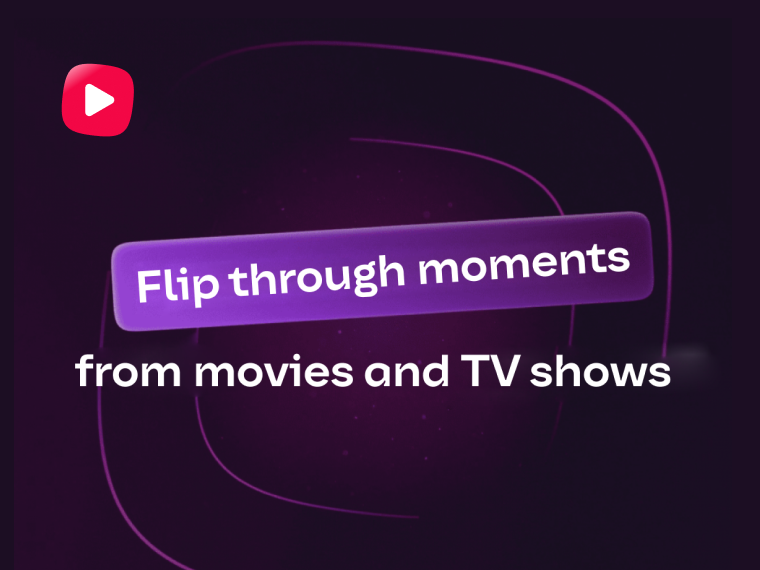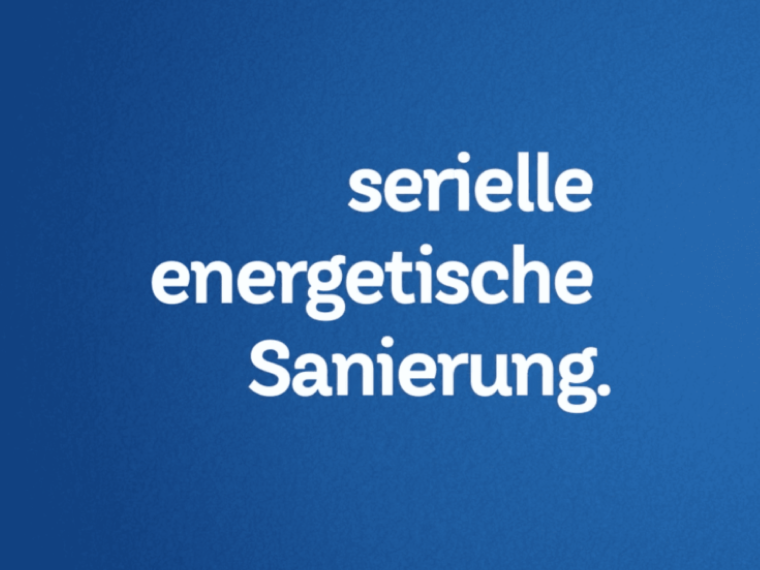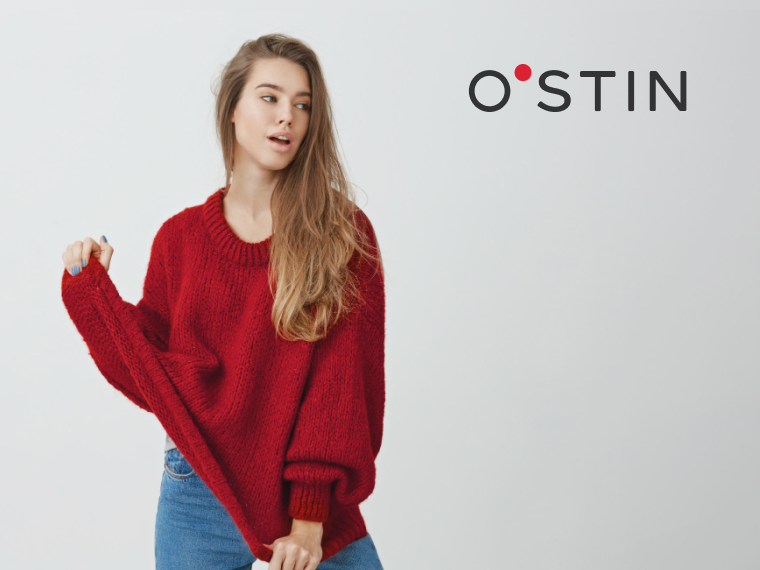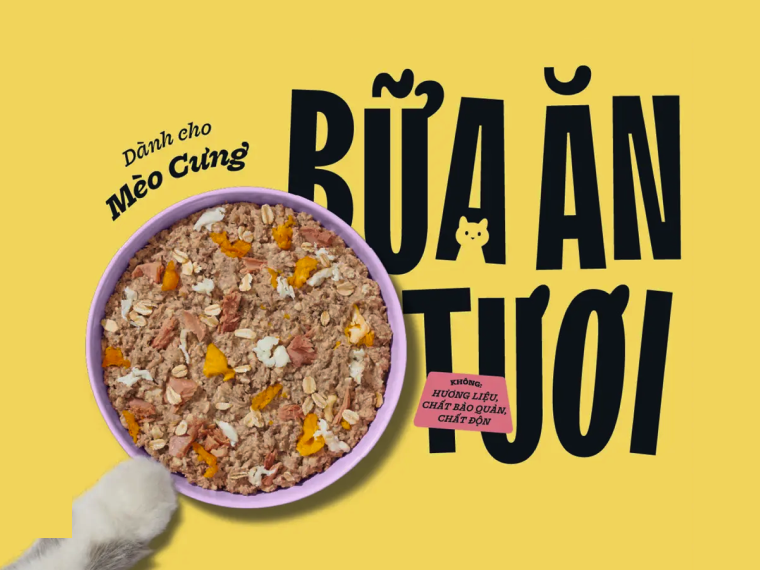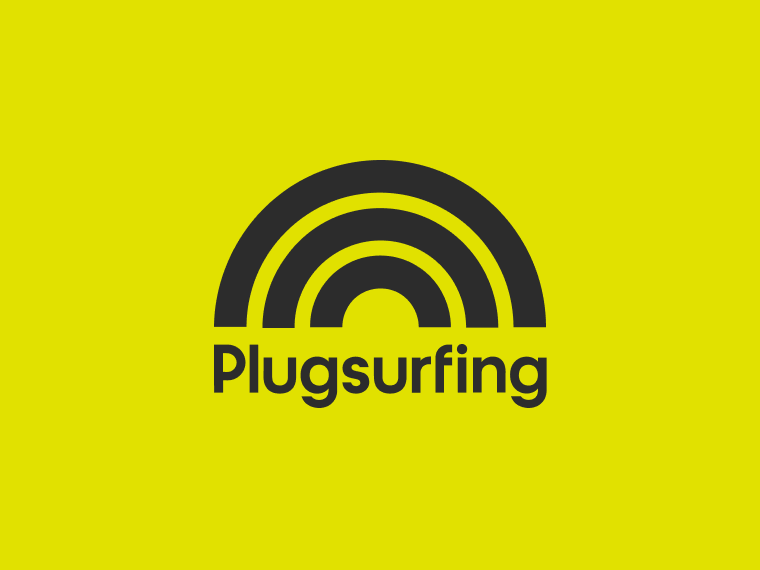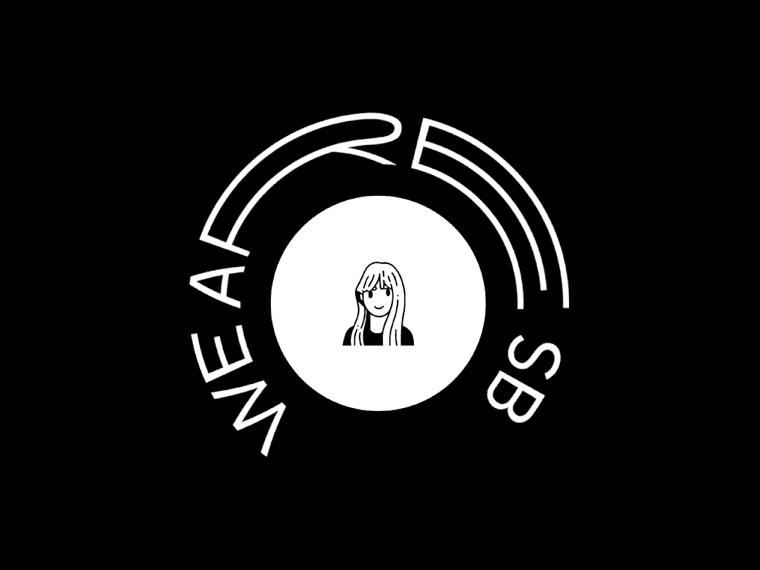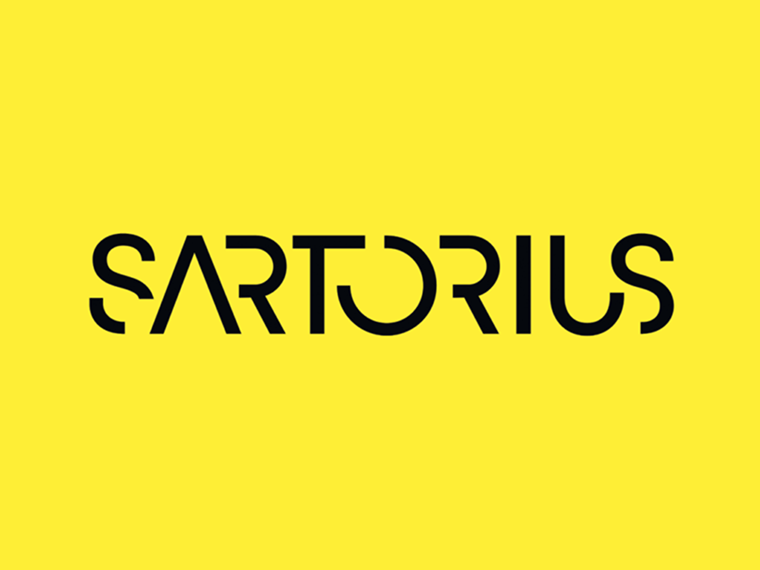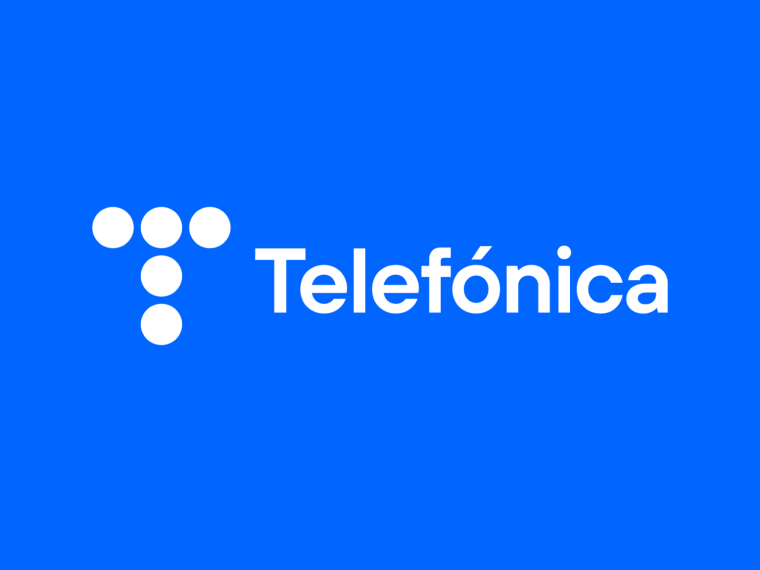
Fonderie Polices sur mesure
La voix de votre marque en typographie
Nous pouvons adapter n’importe quelle police TypeType pour qu’elle corresponde parfaitement à votre projet ou concevoir une typographie entièrement nouvelle qui incarne les valeurs de votre entreprise.
Options de personnalisation
Personnalisation légère
• Renommage de la police
• Ajout d’un logo au jeu de caractères
• Remplacement des caractères principaux par des alternatives
• Modification graphique de glyphes individuels
Personnalisation standard
• Renommage de la police
• Ajout d’un logo au jeu de caractères
• Modification graphique de glyphes individuels
• Création de nouveaux styles
Personnalisation avancée
• Renommage de la police
• Ajout d’un logo au jeu de caractères
• Croquis
• Modification graphique de glyphes individuels
• Conception d’une police basée sur une police TypeType
Création de police sur mesure
• Nom unique de la police
• Ajout d’un logo au jeu de caractères
• Croquis
• Création d’une police personnalisée
• Ajustements techniques: mastering, kerning, hinting, fontinfo
Personnalisation légère
Choisissez la personnalisation légère si vous souhaitez utiliser une police TypeType avec de petites modifications. Nous ajusterons certains caractères et remplacerons les glyphes de base par des alternatives. Nous intégrerons également votre logo et renommerons la police selon votre marque.
LEG
Une entreprise immobilière allemande
Plugsurfing
Un développeur d’une application mobile permettant de trouver des bornes de recharge pour véhicules électriques
Personnalisation standard
Si vous souhaitez utiliser une police de notre collection tout en ayant besoin de styles supplémentaires, choisissez l’option de personnalisation standard. Nous modifierons des caractères individuels et ajouterons de nouveaux styles afin de répondre à vos objectifs. La police personnalisée sera renommée : son nouveau nom sera associé à votre entreprise ou à votre projet. De plus, nous intégrerons votre logo dans le jeu de caractères de la police.
Telefonica
L’une des plus grandes entreprises de télécommunications au monde
PetChoy
Une entreprise proposant des repas premium pour chats et chiens
SHIFTBRAIN
Un studio japonais de développement numérique et de design
Personnalisation avancée
La personnalisation avancée consiste à concevoir pratiquement une nouvelle police avec plusieurs styles, en utilisant une police TypeType de votre choix comme base. Dans le même temps, les formes graphiques des caractères seront entièrement transformées. La police recevra un nouveau nom associé à votre entreprise ou à votre projet, et nous intégrerons également votre logo dans le jeu de caractères.
Sartorius
Un fournisseur international d’équipements pharmaceutiques et de laboratoire
OSTIN
Une grande chaîne de magasins de vêtements
Création d’une police à partir de zéro
Les polices sur mesure sont un élément clé des grandes marques. Nous créons des typographies personnalisées en tenant compte des spécificités de chaque projet.
Nous pouvons concevoir une police unique ou une famille complète. Par exemple, il est fréquent de développer une police pour les titres et une autre pour le texte.
Le processus inclut recherche, croquis, validation, puis développement graphique et technique.
Création de la police Ivi Sans Display pour IVI — cinéma en ligne
Cinéma en ligne
Personnalisation de police
Parfois, même si une police vous plaît visuellement, elle ne correspond pas parfaitement à votre projet. TypeType propose une solution : la personnalisation de police.
Toute police de la collection TypeType peut être adaptée et personnalisée selon les besoins spécifiques de votre projet. Nous pouvons apporter des modifications légères comme des transformations plus approfondies. Pour en savoir plus, consultez nos options de personnalisation.
Options de personnalisation
À droite, vous pouvez découvrir quelques exemples de personnalisation réalisés par l’équipe TypeType. La version originale de la police est affichée par défaut. Cliquez sur le bouton pour voir la version personnalisée.
Espacement personnalisé 1
Espacement personnalisé 2
Alternatifs par défaut
Graisse personnalisée
Version condensée
Hinting
Le hinting (également appelé « instructing ») consiste à utiliser des instructions mathématiques pour ajuster l’affichage d’une police vectorielle afin qu’elle s’aligne correctement sur une grille rasterisée.
À basse résolution d’écran, le hinting est essentiel pour garantir un texte clair et lisible. Il peut être associé à l’anticrénelage ainsi qu’au rendu subpixel (sur les écrans à cristaux liquides) pour améliorer encore la netteté.